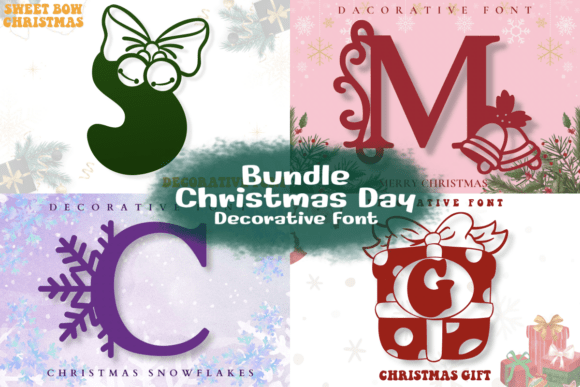
Christmas Day Bundle
Trouver les bons éléments de conception peut être un défi, mais Christmas Day Bundle propose une collection exceptionnelle qui rehausse instantanément votre travail.
Que vous créiez des produits POD (impression à la demande), des invitations de mariage ou des visuels pour les réseaux sociaux, Christmas Day Bundle est un choix idéal.